8 أفضل خطوط الشكر لك لتلتهم
نشرت: 2020-11-19عندما يقترب موسم العطلات ، قم بعمل أسباب لتجميع المستندات والمواد الترويجية. سواء كانت نشرة ذات طابع ديك رومي لإخبار مكان عملك بموعد حفل المكتب أو دعوة متخصصة إلى عشاء العائلة ، فهناك فرصة جيدة لأنك لا تتبع تصميمًا وحشيًا يذكرهم بمذكرة فدية أو قائمة Craigslist ميلادي. تريد إضفاء الإثارة على المرئيات تمامًا كما لو كنت ستضيف نكهة إلى فطيرة اليقطين. لا يمكننا أن نلومك. ونحن نفعل الشيء نفسه! وهذا هو السبب في أننا خرجنا ووجدنا ليس فقط خطوط عيد الشكر الأكثر أناقة وإثارة للحميمية الموجودة هناك ، ولكن أيضًا بعضًا من أكثرها غرابةً وأكثرها متعة. لذا - مرة أخرى مثل عشاء عيد الشكر - دعنا نتعمق.
1. توقيت تركيا
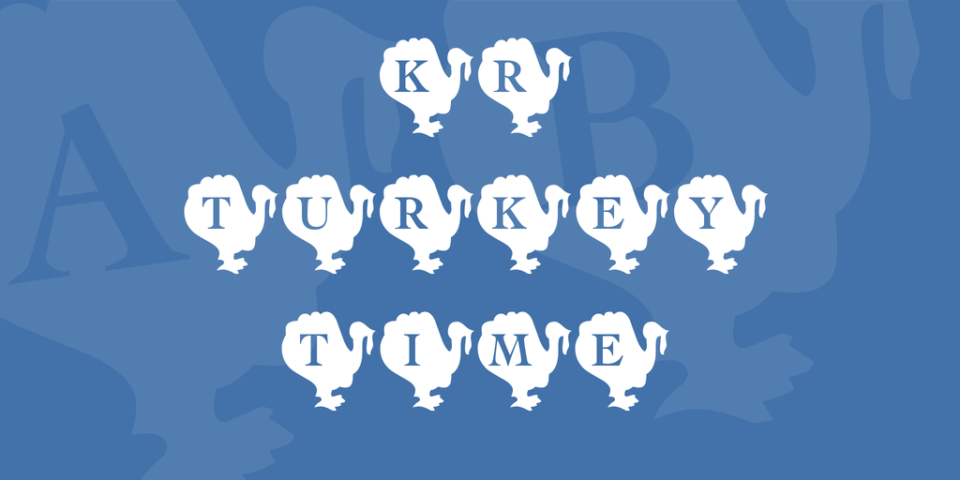
عندما تبحث عن خط عيد الشكر الذي لا يترك أي مجال للشك حول الغرض من تصميمك ، فأنت بحاجة إلى تنزيل KR Turkey Time. لا يتم إنشاء الصور الرمزية في هذا الخط للمخطوطات أو المستندات الطويلة ، ولكن عندما تحتاج إلى إبراز شيء ما وجذب الانتباه ، لا يمكنك أن تخطئ هنا. من المؤكد أن جمهورك سوف يلتهم هذه الديوك الرومية. (آسف ، لم نتمكن من المقاومة.)
2. نسيم الخريف
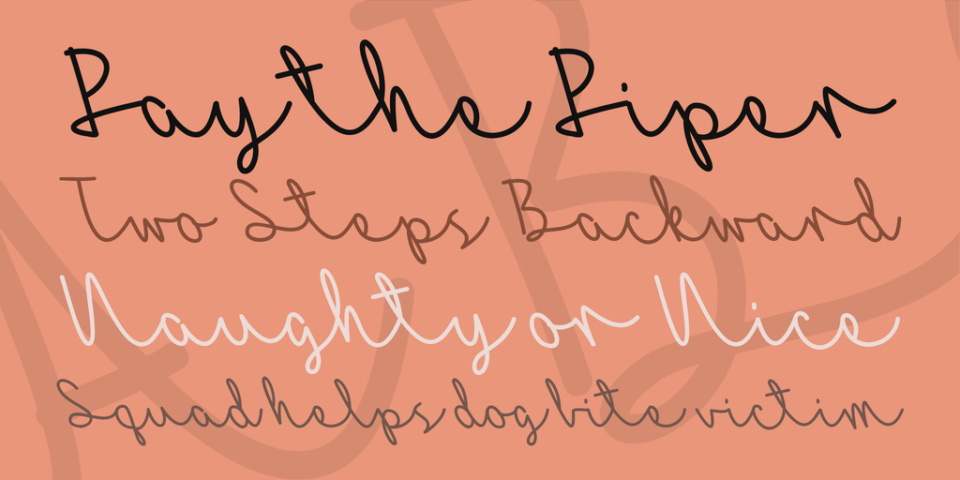
عندما تحتاج مستندات عيد الشكر الخاصة بك إلى القليل من الأسلوب والفئة ، فإن Autumn Breeze هو أحد أفضل الخيارات. كخط بنمط البرنامج النصي ، يبدو تلقائيًا أكثر تجميعًا من خط التحايل. لا يبدو الأمر شخصيًا فقط ويخلق الجو العائلي الذي تزدهر فيه العطلة ، ولكنه أيضًا مقروء بما يكفي بحيث يمكنك إدراجه في المستندات الاحترافية لهذا الموسم.
3. أيام الخريف
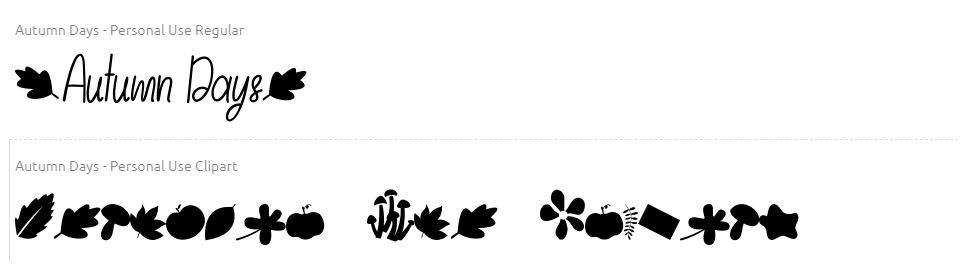
تأخذ أيام الخريف ما يناسب أول خطين أعلاه وتجمعهما في مجموعة واحدة رائعة من الصور الرمزية. لديك خط مريح ومكتوب يدويًا وأيضًا مجموعة من صور الرسوم المتحركة والأيقونات التي يمكنك استخدامها لتزيين وتحسين أي تصميمات تقوم بتجميعها معًا. إذا لم تكن معتادًا على الصور الرمزية للقصاصات الفنية في الخطوط ، فإنها تعمل بشكل جيد بشكل لا يصدق كإضافات زخرفية للتصميمات لأنها في الأساس متجهات يمكن تغيير حجمها إلى أي حجم دون فقدان الدقة. لن تحتاج إلى تحرير الصور أو إضافة خطوات إضافية لإنهاء تصميمك. لذا فإن أيام الخريف متعددة الاستخدامات بشكل لا يصدق وتستحق المشاهدة.
4. الزبدة
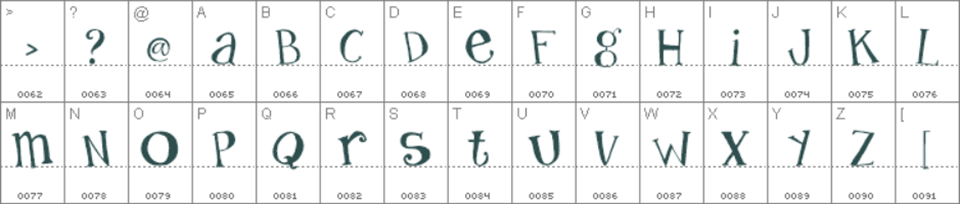
لا تعد كريمة الزبدة واحدة من أفضل عناصر عشاء عيد الشكر فحسب ، بل إنها الآن أيضًا واحدة من أفضل العناصر في دعواتك ونشراتك الإعلانية أيضًا. سواء أكنت ترسل رسائل خاصة إلى كل فرد من أفراد عائلتك لإخبارهم بمدى قصدهم لك أو مجرد نشرة في المكتب لإخبار من سيحضر ما إلى الطعام ، فإن FB Buttercream لن يبدو في غير محله. يعد خط الشكر هذا مناسبًا للرؤوس أو النص الأساسي ، وهو أحد الخيارات الأكثر تنوعًا.
5. قبعات الحزب البيوريتاني
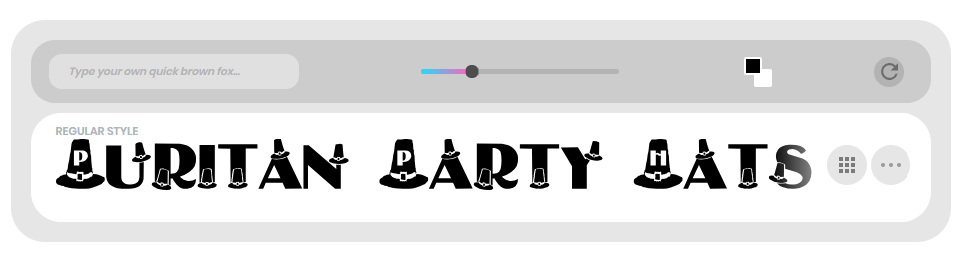
عندما تفكر في عيد الشكر في أمريكا ، تتبادر إلى الذهن بالتأكيد صورة واحدة غير الديك الرومي. قبعات الحاج. هذا هو السبب في أن خط Puritan Party Hats مثالي للغاية. بعد كل شيء ، اشتهر المتشددون بإقامة أفضل الحفلات. حسنًا ... حسنًا ، ربما لا ... ولكن هذا الخط بالتأكيد سوف يضفي الحيوية على أي غرفة. لا يقتصر الأمر على كونه خطًا قابلاً للقراءة تمامًا ، ولكنه غريب بما يكفي لإثارة روح العطلة في أي مستند أو تصميم أو موقع ويب تستخدمه فيه. على الرغم من أنك لن تكتب أي رسائل بريد إلكتروني كاملة أو قصص قصيرة تحت عنوان العطلة بهذه القبعات ، إلا أنك ستلفت انتباه جمهورك تمامًا وستخبرهم على الفور بأنهم سيحصلون على نوع من أنواع العطلات. أليس هذا هو سبب الثقب لاستخدام خط Thanksgiving في المقام الأول؟
6. البازلاء إيلي بيلي
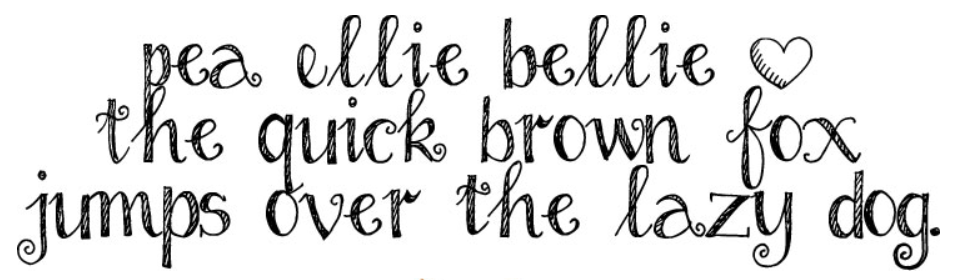
ربما يكون الخط الذي يحمل الاسم الأكثر متعة ليقوله ، Pea Ellie Bellie هو خط مبهج يمكن أن يجعل أي مستند يبدو منزليًا ودافئًا مع القليل من العمل. ما عليك سوى إلقاء نظرة على الصور الرمزية أعلاه وإخبارنا أنك لن تعتقد على الفور أن أي شيء مطبوع بها كان مخصصًا لك فقط بأكبر قدر ممكن من الحب. انت ترغب. لهذا السبب نعتقد أن البحث عن خط عيد الشكر الخاص بك يمكن أن ينتهي هنا مباشرةً إذا كنت ستذهب إلى المنزل الريفي لعيد الشكر. سيعرف ضيوفك على الفور أنه يتم الترحيب بهم بأذرع مفتوحة.
7. حصاد الخريف
الجميع يحب Wingdings. لذلك عندما يتعلق الأمر باختيار خط عيد الشكر ، فإن Autumn Harvest Dings لا تحتاج إلى تفكير. كما ذكرنا أعلاه ، فإن خطوط الرموز مذهلة لتزيين المستندات لأن الصور قابلة للتطوير في أي محرر مستندات يتيح لك ضبط حجم الخط. يمكن إدخالها بسرعة وسهولة ، والتلاعب بها من قبل أي شخص ليس لديه صورة رسمية أو تدريب على التصميم. (بعد كل شيء ، من منا لا يعرف كيفية التغيير من 12pt إلى 112؟). تغطي هذه المجموعة الخاصة من الحروف الرسومية سلسلة معايير عيد الشكر ، من الوفرة الفائضة ، ودلاء الذرة ، وعباد الشمس ، وجرف الأوراق إلى أكوام ليقفز إليها الأطفال بعد أن يملأوا أنفسهم. إذا كان لديك تصميم لعيد الشكر يحتاج إلى القليل (أو الكثير!) من الذوق الإضافي ، فإن هذه الضربات ستفعل ذلك.
8. شكرا على العطاء
شيء ما عن الأعياد يخرج الطفل فينا جميعًا. على الأقل قليلا. باستخدام خط Thanks For Giving ، يمكنك تذكير من يقرأها بالاستسلام لهذا الشعور والسماح لروح العطلة بالسيطرة. دائمًا ما تبدو خطوط الكتابة اليدوية أكثر دفئًا وأكثر خصوصية ، كما أن برنامج Thanks for Giving يكون خشنًا بدرجة كافية حول الحواف لمنحه جودة تشبه الأطفال ، ولكن دون أن يبدو في غير محله في المستندات الاحترافية. من الدعوات إلى اتخاذ إجراء للأعمال الخيرية ، يُعد Thanks For Giving خطًا لعيد الشكر يشتمل بالكامل على أفضل أجزاء موسم العطلات ويعيدها إلى البستوني.
بغض النظر عما تصممه ، نأمل أن تكون ممتنًا بقدر امتناننا لأن هذه الخطوط موجودة لجعل روح العطلة تنبثق مباشرة من الصفحة أو الشاشة. في الوقت الذي يقوم فيه الجميع وأختهم بعمل منشورات وملصقات ودعوات تحت عنوان العطلة ، فإن أخذ أي من خطوط عيد الشكر هذه وخبزها في خطك سيجعل الناس ينتبهون بالتأكيد.